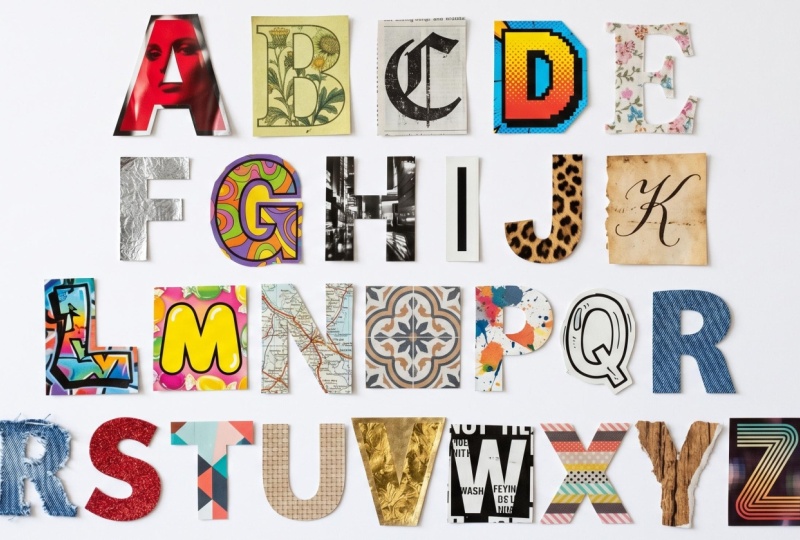
1. Introduction: Bienvenue dans ce cours, Conception avec du texte,
Typographie pour les non-concepteurs. Où je vais vous présenter
quelques-uns de mes trucs
et astuces pour
utiliser les caractères et les polices de caractères. Nous parlerons de l'
émotion qui se cache derrière une police de caractères. Comment mettre en page du texte. Vous pouvez inciter votre spectateur à
lire davantage
et obtenir des conseils sur la façon de
travailler avec le corps du texte, afin que les
utilisateurs puissent le lire et le digérer facilement. Ce cours s'adresse
spécifiquement aux non-designers. Ceci est destiné aux personnes
qui utilisent du texte pour des présentations ou des graphiques de réseaux
sociaux, mais qui n'ont aucune
formation en typographie. À la fin de ce court cours, vous serez plus
à l'aise dans l'utilisation de la
typographie et dans la manière de l'utiliser efficacement pour communiquer le bon
message à votre public. Bonjour. Je suis Faye Brown
et j'enseigne sur Skillshare depuis 2012. Je suis un
spécialiste du
design graphique et de l'image de marque basé au Royaume-Uni. Je suis un grand passionné de typographie qui pourrait parler de
polices de caractères toute la journée. Cependant, dans ce cours, je vais résumer
cela en un court
cours de 20 minutes qui vous donnera
le savoir-faire nécessaire pour utiliser la typographie
plus efficacement,
alors plongeons-nous dans le vif le savoir-faire nécessaire pour utiliser la typographie du sujet.
2. Qu'est-ce que la typographie ?: Qu'est-ce que la typographie ? En termes simples, la typographie
est l'art d'organiser ou de concevoir des formulaires de lettres. J'aime décrire la typographie
comme votre voix visuelle, même si ce n'est pas vraiment ce que signifie
beaucoup de graphisme. C'est communiquer un message
sans avoir à parler. Nous prenons tout cela en compte visuellement. La connaissance de
quelques trucs
et astuces de typographie est un outil très
utile. J'ai vraiment été
fascinée par la typographie lorsque j'ai fait mes études de
graphisme. C'est un très vaste domaine à couvrir. Aujourd'hui, nous allons nous concentrer
principalement sur les polices de caractères et sur la façon dont chacune peut avoir sa
propre personnalité. Au fur et à mesure, je vais vous
présenter certains termes typographiques
et quelques conseils sur la façon de mettre en page
des blocs de texte intéressants pour le
lecteur. Vous
pouvez choisir parmi un
certain nombre de projets pour ce cours. Vous pouvez choisir l'un ou l'
ensemble d'entre eux si vous le souhaitez. La première sera de
partir à la chasse à l'alphabet. Vous pouvez emporter un appareil photo
et
rechercher chaque lettre
de l'alphabet, idéalement tous les
styles. En voici une que j'ai faite lors d'un
récent séjour à Londres. Ce projet vous
aide vraiment à réaliser les différents
styles de polices de caractères. Au fur et à mesure que vous réfléchissez aux
styles utilisés quoi et comment vous sentez-vous avec ces
types de visages ? C'est peut-être une boutique. La police de caractères lui donne-t-elle un aspect cher ou plus
économique ? Est-ce que ça donne un aspect
sérieux ou amusant ? Est-ce que la police de caractères
semble accessible ou peut-être un peu effrayante ? La police de caractères est-elle facile à lire ? Sinon, vous avez peut-être envie de réaliser ce
projet un jour de pluie, alors vous pourriez utiliser
des magazines pour trouver toutes les lettres
de l'alphabet. Essayez d'utiliser différents magazines et voyez comment ils utilisent les
polices de caractères de différentes manières en fonction du sujet. magazine Minecraft de mon fils utilise des polices de caractères
très différentes pour Ideal Home Magazine, par
exemple. Il suffit de penser à tout cela pendant
que vous collectez vos lettres. Une alternative
est de choisir une lettre, peut-être la première
lettre de votre nom,
et d' essayer de trouver autant
d'exemples
différents de cette lettre que possible. Cela peut être plus difficile
selon votre nom. Voici un exemple de quelques
F que j'ai trouvés sur pinterest.com. Mais c'est plus amusant
si vous pouvez sortir et
parcourir les magazines. Si vous pouvez trouver un mélange de lettres
majuscules et minuscules, ce serait bien. Les lettres majuscules sont des lettres majuscules. Elles sont appelées
majuscules car à
l'époque de l'utilisation de caractères métalliques, les lettres majuscules étaient
conservées dans le tiroir supérieur. Juste au cas où vous vous demanderiez pourquoi ils étaient appelés majuscules. En choisissant une lettre, cela vous permet de voir
les différentes manières dont ces lettres peuvent être dessinées, même si les
formes de base seront les mêmes. Les ressources de
classe comprennent également
un PDF contenant des alphabets et
des chiffres de tous les styles. Vous le trouverez dans
l'onglet Ressources. Si vous avez du papier calque ou
une fine feuille de papier blanc, essayez de dessiner
par-dessus ces lettres. C'est un très bon moyen de
comprendre les formes des lettres et les différents styles
de polices de caractères. De plus, ceux qui sont un peu
plus confiants dans le dessin, essayez de les redessiner
sans tracer. Ce sont vos projets. Je vais continuer à y revenir,
mais parlons maintenant plus
en profondeur de la
façon dont les mais parlons maintenant plus
en profondeur de la polices de caractères peuvent avoir
leur propre personnalité et de la façon dont la police
que vous choisissez peut changer la façon dont vous lisez un mot.
3. Choisir des caractères: Choisir la bonne police de caractères. Une police de caractères peut-elle réellement susciter une émotion ? Jetons un coup d'œil. J'aime utiliser le mot amour
et école pour cet exercice. Commençons par l'amour. Voici quatre polices de caractères différentes illustrant exactement
le même mot. Que ressentez-vous chacun d'entre eux ? La couleur peut également jouer un
rôle important dans la conception visuelle, mais je n'inclus volontairement pas la
couleur dans ces options, c'est uniquement basé
sur la police de caractères. Mettez la vidéo en pause si vous le souhaitez et prenez des notes
mentales sur la façon dont ces polices de caractères peuvent aider à illustrer différentes
formes d'amour. Je pense qu'en haut à gauche, c'est un amour très amical. C'est assez classique. C'est un peu marrant,
si c'est un mot. C'est un amour fluide. Le coin supérieur droit est
quelque peu différent. Ça a l'air un peu
effrayant, un amour dur. Je peux l'imaginer sur une
pochette d'album d'un groupe de rock,. L'amour en bas à gauche
est assez moderne, il est très confiant et audacieux. Ensuite, optez pour une solution douce avec
les bords incurvés et la rondeur de
certaines formes et formes. L'amour en bas à droite semble
très innocent et enfantin. C'est l'amour qu'un tout-petit peut avoir pour son ours en peluche
préféré. que vous ayez
vu ces mots exactement de la même
manière que moi ou non, Peu importe que vous ayez
vu ces mots
exactement de la même
manière que moi ou non,
mais
je suppose qu'il y avait similitudes entre
nos pensées. Vous ne
verrez probablement pas le coin supérieur droit sur trop d'invitations
de mariage. En choisissant simplement
différentes polices de caractères, nous pouvons façonner la façon dont le lecteur
pourrait s'identifier au mot. Regardons le mot école, qui n'est pas
un mot si émouvant. Encore une fois, mettez la vidéo en pause
et réfléchissez à manière dont vous vous connectez à ces options. votre avis, à quoi pourrait ressembler chaque
école ? Celui en haut à gauche pour moi a l'air très traditionnel
et correct. Je m'attendrais
à ce que l'école soit bien établie et sérieuse dans son
approche de l'éducation. Celui en haut à droite
a l'air plus amusant. Ce serait peut-être
bien pour l'école de danse. En bas à gauche, celle-ci me
rappelle une école de sport
américaine, j'ai l'impression que c'
est une école très sportive. En bas à droite, on
dirait peut-être une école de théâtre, quelque chose d'assez bruyant
et peu excitant. Vous pouvez également faire cet exercice
avec votre nom. Disons que je
dessinais un logo pour un certain Charlie Hooper. Nous ne savons pas quel est le
sexe de Charlie, nous ne savons pas ce que fait Charlie, mais simplement en
regardant ces polices de caractères, nous pourrions commencer à nous faire des
idées sur
ce que fait Charlie. Vous pouvez essayer de trouver
une police de caractères pour vous-même. Il existe un excellent site Web
appelé Font Squirrel, qui regorge de polices de caractères gratuites. Vous pouvez cliquer sur certains
termes ici comme point
de départ,
puis cliquer sur Test Drive où vous pouvez saisir votre nom et
voir à quoi il ressemble. Pense à ta personnalité. Est-ce que cela vous convient ? Celui-ci est probablement un peu trop chic pour moi, à titre d'exemple. J'ai aimé le fait qu'il soit assez
sympathique et audacieux, mais
il est un peu trop beau et peut-être un peu trop et c'est en fait
assez difficile à lire. un autre excellent site Web
pour rechercher creativemarket.com est un autre excellent site Web
pour rechercher des polices de caractères. Vous pouvez rechercher des polices
et, si vous cliquez sur un ensemble, vous pouvez à nouveau les
tester toutes en même temps. Ceux-ci coûtent de l'argent, mais c'est quand même
un exercice assez amusant à faire. Cela m'aide à
les comparer facilement et voir ce qui me convient le mieux. Cela provenait d'un bundle moderne, mais vous devriez peut-être opter
pour quelque chose de beaucoup plus décoratif et original
comme celui-ci. Pensez simplement à
votre personnalité et au style qui pourrait vous convenir. C'est essentiellement le
processus que je passe par lorsque je crée
des logos. Réfléchir à la personnalité
des lettres et à la façon dont elles reflètent l'entreprise ou personne pour laquelle je dessine. Essaie par toi-même. Ce qui vous aidera à
démarrer, c'est d' en savoir un
peu plus sur classifications
de
types, du service au
libre-service, en passant par les polices de script
et d'écriture manuscrite. Nous allons maintenant
examiner quelques-unes d' entre elles pour vous
aider dans vos recherches.
4. Classifications de type: Serif. Une police Serif comporte de petits traits à la
fin des caractères. Les empattements sont généralement
associés à des
polices plus traditionnelles telles que Times et Garamond, mais la plupart des
polices les plus modernes utilisent des empattements, qu'
ils soient entre crochets,
comme Garamond ici, ou en dalle Serif comme Rockwell ou
Wedge Serif comme Birch. De nombreux livres sont écrits à l'aide polices Serif
traditionnelles telles que Garamond. Les lettres séreuses aident à former un lien
entre chacune des lettres, ce qui permet au lecteur de suivre une ligne ou un
paragraphe de texte. Les polices
Serif plus traditionnelles peuvent donner à quelque chose de
très professionnel, digne de confiance et
établi, mais elles peuvent aussi donner une impression d'ennui. Sans Serif. Sans Serif est simplement une police de caractères sans Serfs,
sans, c'est-à-dire sans. La police de caractères
Sans Serif la plus célèbre est peut-être Helvetica, comme on peut le voir ici dans le métro de
New York. Une famille de polices de caractères simple comme cette copie corporelle qui se trouve à
Montserrat est facile à lire et facilite la lecture
pour le lecteur. Nous voyons souvent des
polices de caractères sans serif utilisées sur les sites Web, bien que les serfs fassent
un petit retour. polices de caractères sans serif
en général
communiqueront une approche
un peu plus moderne
de l'entreprise, conviviale et accessible. Si vous visez
un marché plus jeune, vous pouvez opter pour un style
Sans Serif. Toutes les polices de caractères
correspondent généralement à un serif ou sans empattement, mais il existe d'autres styles
à prendre en compte. polices de caractères de style script
ont été développées
au XVIIe siècle
sur la base de techniques d'écriture
utilisant la plume et l'encre. Depuis cette époque,
d'autres styles de script se sont développés et
sont devenus très populaires. Les styles de script peuvent vraiment varier dans leur message, allant de la forme et de l'élégance à
une lettre noire lourde, audacieuse et bruyante. Les styles de bandes dessinées peuvent être
amusants en fonction de l'utilisation. Essayez d'éviter Comic Sans. Comic Sans a été
utilisé, surutilisé et
également utilisé pour des
choses inappropriées, comme des panneaux d'avertissement. Il y a un
panneau d'avertissement dans notre ville concernant l'électrocution
et c'est dans Comic Sans. Il a une mauvaise
réputation auprès des designers. Bien qu'apparemment,
c'est l'une des polices de caractères
les plus faciles à lire
pour les enfants. Les polices de caractères décoratives
reprennent de nombreux styles, tels que Budmo
Jiggler et Rosewood, elles ne seraient utilisées que
pour vraiment attirer l'attention, donc des titres, des affiches et peut-être des
logos de la bonne façon. décoration peut également
intégrer des styles de scripts. Les styles de machines à écrire comme celui-ci sont assez
explicites. Ce style peut
très bien fonctionner pour les conceptions de
style de définition de
dictionnaires. Les styles de pochoir sont généralement polices de caractères présentant des ruptures
dans les formes des lettres. Ils sont souvent utilisés pour des références de style militaire
ainsi que pour des documents top secrets. L'affichage de nombreux
styles précédents dont nous avons parlé relèverait de cette catégorie mais lors de recherches de polices, cette catégorie afficherait options idéales
pour les textes plus volumineux, donc les titres et des affiches, quelque part fonctionnent aussi pour les
logos. Écrit à la main. Elles peuvent également s'intégrer au script en
raison du style, mais les polices de caractères manuscrites
sont très populaires et peuvent ajouter une touche conviviale et
personnalisée au texte. Ce n'est pas seulement la
police de caractères qui peut aider à communiquer
un message. L'utilisation de la taille et du poids peut également
être utilisée de manière très efficace. Jetons un coup d'œil
à la vidéo suivante.
5. Taille et poids: Taille et poids Les
diapositives suivantes que vous verrez appartiennent souvent à la même
famille sans empattement appelée Gotham. Au sein de cette famille, nous avons poids
léger
à ultra léger. Les formes des lettres sont
basées sur les mêmes formes, mais leur poids leur donne
un aspect très différent. Si nous voulons créer une
sensation de calme et de tranquillité, un poids plus fin
peut être plus efficace, mais si nous voulons crier à propos quelque chose ou avertir les gens
d'un danger possible, un poids lourd et audacieux
saisira attention plus rapide. Nous pouvons également utiliser la taille pour
nous aider dans notre message ici. On peut chuchoter ou crier. Voyons comment cela peut être
utilisé dans ce que l'on appelle la hiérarchie
typographique. C'est à ce moment que nous voulons
inviter le lecteur à
entrer et me laisser suivre les
informations pour éventuellement lire, peut-être comme un article complet. Prenons cela comme
un bref exemple. Supposons que vous ayez vu
ces deux carrés apparaître sur
les réseaux sociaux ou sur un site Web, lequel êtes-vous
le plus susceptible de lire ? Celui de droite vous
invite à entrer. Cela vous donne une idée de ce dont
le reste du paragraphe pourrait parler sous forme de
blocs d'informations faciles à assimiler. Voyons comment les concepteurs de
magazines y parviennent dans le cadre de la conception de mises en page. Nous voyons le titre. C'est le
plus gros texte de la page. Nous voyons le sous-titre, qui est probablement le deuxième plus gros texte de la page. Nous avons également un extrait
que vous lirez probablement
après le sous-titre. À ce stade, vous savez probablement que si vous voulez lire
l'article en entier, le reste du texte
est appelé corps du texte. Notre œil a contourné
les informations clés très rapidement, grâce à la disposition du
texte. En ce qui concerne de telles
mises en page, nous voulions nous assurer que
le texte est facile à lire. Certaines typographies sont en fait
assez difficiles à lire, même si vous pouvez vous en sortir
avec de plus grandes tailles. Cette amitié typographique
est assez amusante. En tant que police d'en-tête, elle fonctionnerait bien sur une affiche. Il a l'air sympathique et original. Il est également audacieux et facile à lire. Cependant, si nous utilisons ensuite la même police de caractères pour
un bloc de texte, cela devient
soudainement beaucoup
plus difficile à digérer. Cela
me donnerait probablement mal à la tête si je lisais un paragraphe entier écrit
dans cette police de caractères. Pourquoi ça ? Jetons un coup d'œil au corps du
texte et à quelques conseils pour faciliter la lecture de nombreux
textes. abord, nous pouvons choisir une police de caractères avec
ou sans empattement assez simple, rien avec trop de caractères car cela la rendrait
plus difficile à lire. Enregistrez ces polices de caractères
pour les titres. Choisissons la Géorgie. Je l'ai réglé
à une taille de 9 points, ce qui est généralement une
bonne taille pour le corps du texte. Il y a certaines choses
que nous pouvons faire maintenant pour faciliter la tâche du lecteur. Première étape, il s'agit d'un gros bloc de texte
avec de très longues lignes. Il est en fait assez
difficile pour l'œil de lire une ligne de
texte aussi longue. Divisons cela
en deux colonnes. Vous verrez cela dans de nombreux
magazines. Il y aura très rarement
de longues lignes de texte. Entre 10 et 15 mots
sur une ligne, c'est généralement une bonne quantité, soit
60 à 70 caractères. Par caractères, j'
entends les lettres, la ponctuation, les chiffres, etc. L'autre chose que
nous pouvons regarder est l'espace entre
chacune des lignes. C'est ce qu'on appelle diriger. Ces lignes sont
assez rapprochées et donnent au texte
un aspect assez groupé. n'y a pas beaucoup
d'espace blanc autour des lignes pour reposer l'œil. Voyez ce qui se passe lorsque je change l'espacement des lignes de la deuxième colonne, cela semble
soudainement un
peu plus facile à lire. Mais si nous poussons trop loin, cela peut signifier que
j'ai du mal à trouver des renforts au
début de la ligne suivante. Il s'agit de trouver cet équilibre heureux. m'a toujours dit que si vous avez un point de taille de texte d'
environ neuf points, général, un bon espacement des
lignes serait 4 points au-dessus,
soit 12 à 13 points. Cela dépendra
du programme que vous
utilisez et de la facilité avec laquelle il
serait possible de voir ces valeurs. J'utilise beaucoup Adobe Illustrator, mais c'est un programme coûteux. Sur Canva, vous n'avez pas autant de
contrôle sur l'espacement des lignes, alors vous vous
fiez à votre œil. J'espère que ces
petits conseils vous ont aidé
à savoir ce qu'il faut rechercher.
6. crénage: Il y a de nombreux
termes typographiques dont je pourrais parler, mais c'est beaucoup de choses à intégrer, et c'est vraiment quelque chose
à explorer davantage si
vous vous intéressez et c'est vraiment quelque chose
à explorer davantage si
vous vous intéressez à la
conception graphique plus en profondeur. Mais un autre terme
que j'aimerais vous
présenter est le crénage. crénage est l'espace
entre les lettres. Une fois que vous connaîtrez le crénage, vous commencerez à détecter un
mauvais crénage partout. Prenons le mot « commencer ». En général, la plupart des
polices de caractères ont un
crénage prédéfini lorsque vous
les utilisez sur un ordinateur. Mais parfois, les
versions gratuites peuvent ne pas être géniales et vous devez ajuster vous-même
le crénage. Je devrais peut-être rapprocher
ce A du T car il y a
un petit écart. Je crains que si c'
était un gros mot sur une affiche, cet écart ne complique la
lisibilité. Peut-être que cela ressemblera à de
l'art plutôt qu'à un début. Vous pouvez utiliser l'espacement des lettres à notre avantage si nous voulons
ajouter un message à un mot. Pour faire vite, je pourrais réduire
l'espacement des lettres. De plus, je pourrais le mettre en italique pour qu'il semble
aller de l'avant. Pour ralentir, je pourrais élargir cet espace pour que le
mot soit lu plus lentement. Si vous créez une affiche, je ne
vous suggère pas de commencer à modifier l'
espacement des lettres de chaque mot, car cela
commencera à paraître désordonné
et incohérent. Mais le crénage est un
bon terme à
connaître lorsqu'il s'agit
de typographie.
7. Vos projets: Revenons donc
sur ces projets. Vous en savez maintenant beaucoup
plus sur les polices de caractères, l'émotion qu'une
police de caractères peut transmettre et les différentes
classifications des polices de caractères. Sortez et explorez et voyez
combien vous pouvez en trouver. Prenez note mentalement des
polices de caractères qui ont été
utilisées pour quoi ? Est-ce qu'ils aident à faire passer
le message ? Ou est-ce qu'un meilleur style
de police fonctionnerait mieux ? Créez vos alphabets à partir de photos ou de magazines et amusez-vous
à mieux connaître les lettres. Alors pourquoi ne pas essayer de
créer votre propre police de caractères ? Vous pouvez utiliser un site
comme calligraphr.com qui propose une inscription, mais vous pouvez
commencer gratuitement. Ensuite, vous pouvez imprimer le formulaire et le remplir avec
vos propres lettres. Vous pouvez simplement
dessiner vos propres lettres à la main. Pensez aux
formes des lettres lorsque vous faites cela, certaines lettres peuvent prendre
quelques coups pour être parfaites. Vous pouvez utiliser des Lego,
des découpes en papier, des blocs de pâtes, tampons imprimés
de pommes de terre,
des pierres, des rubans, des pièces de monnaie. Utilisez peut-être vos initiales
pour trouver
des façons créatives
de créer des lettres. Mais surtout, amusez-vous
un peu.
8. Conclusion: C'est votre introduction
à la typographie. J'ai deux autres cours
sur ce sujet,
The Art of Topography. C'était mon tout premier cours
Skillshare qui aborde ce domaine de
manière beaucoup plus approfondie. Le choix des bonnes polices permet explorer ce domaine un
peu plus loin. J'ai hâte de voir vos
projets car j'adore la typographie et j'adorerais